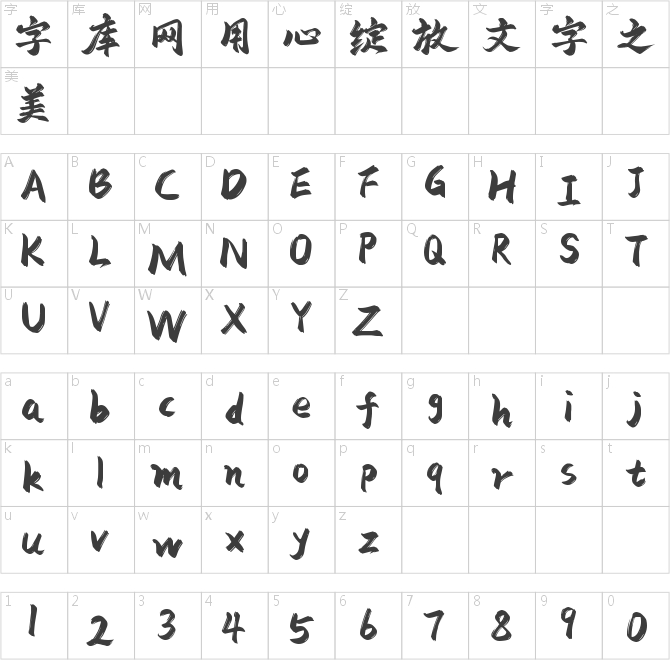
字體名稱: 字庫星球飛揚體
字庫星球飛揚體
字庫星球飛揚體介紹
字體特色 由字庫星球與甜奈網絡聯合研發的書法字體 融合傳統書法美學與現代設計理念 筆畫靈動富有變化,結構流暢自然 兼具藝術氣質與視覺沖擊力 特別適合營造熱情洋溢的氛圍 ? 上海甜奈網絡設計中心版權所有 受《中華人民共和國著作權法》及國際公約保護 授權范圍 ? 免費商用授權(個人/企業) ? 支持商業/非商業用途 ? 禁止二次銷售/轉授權 ? 禁止反編譯/逆向工程 ? 禁止刪除版權標識